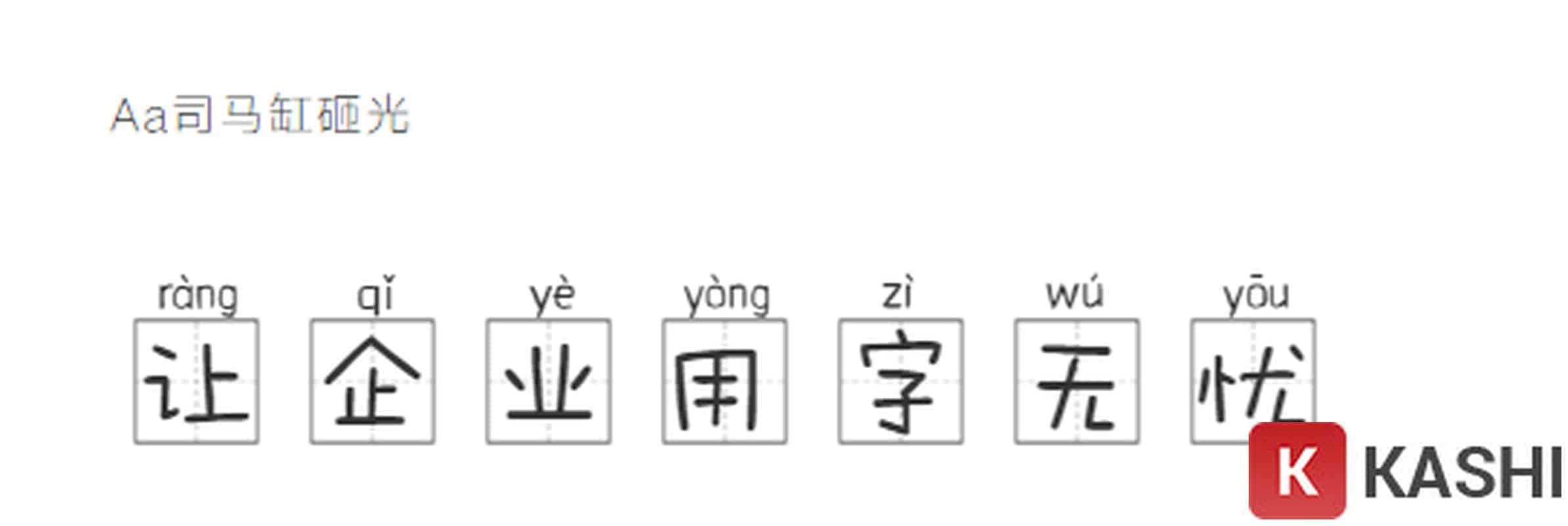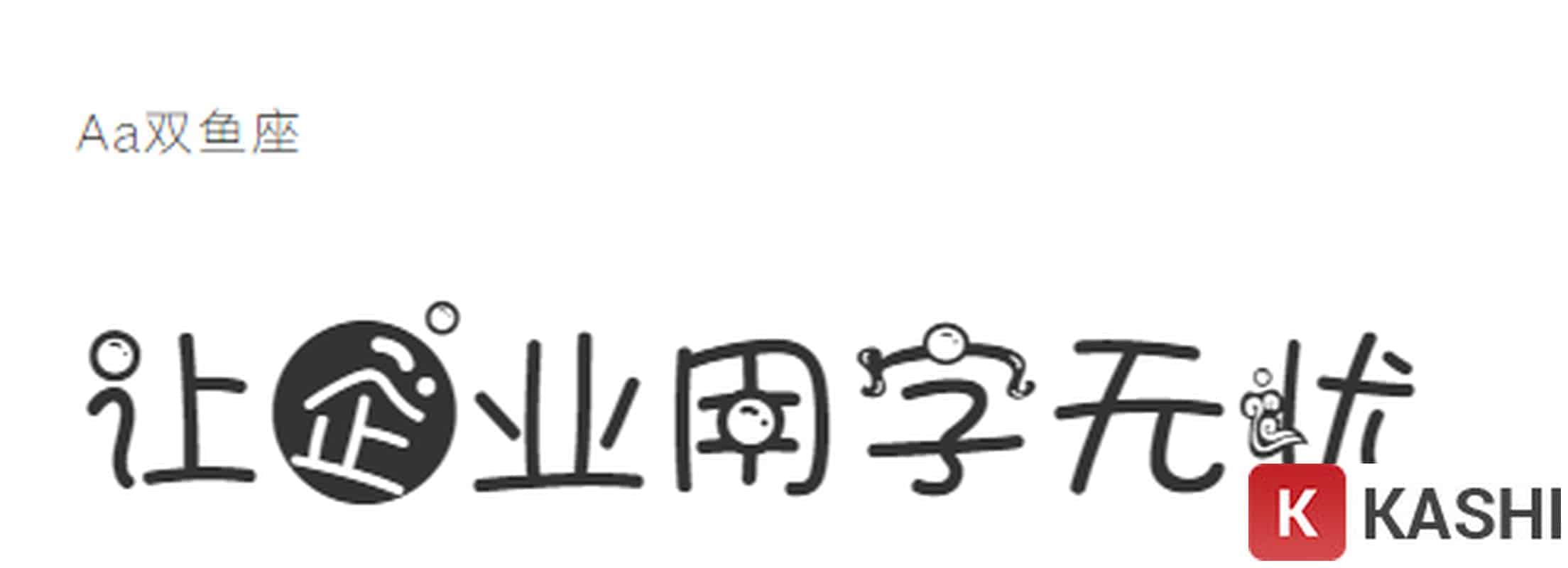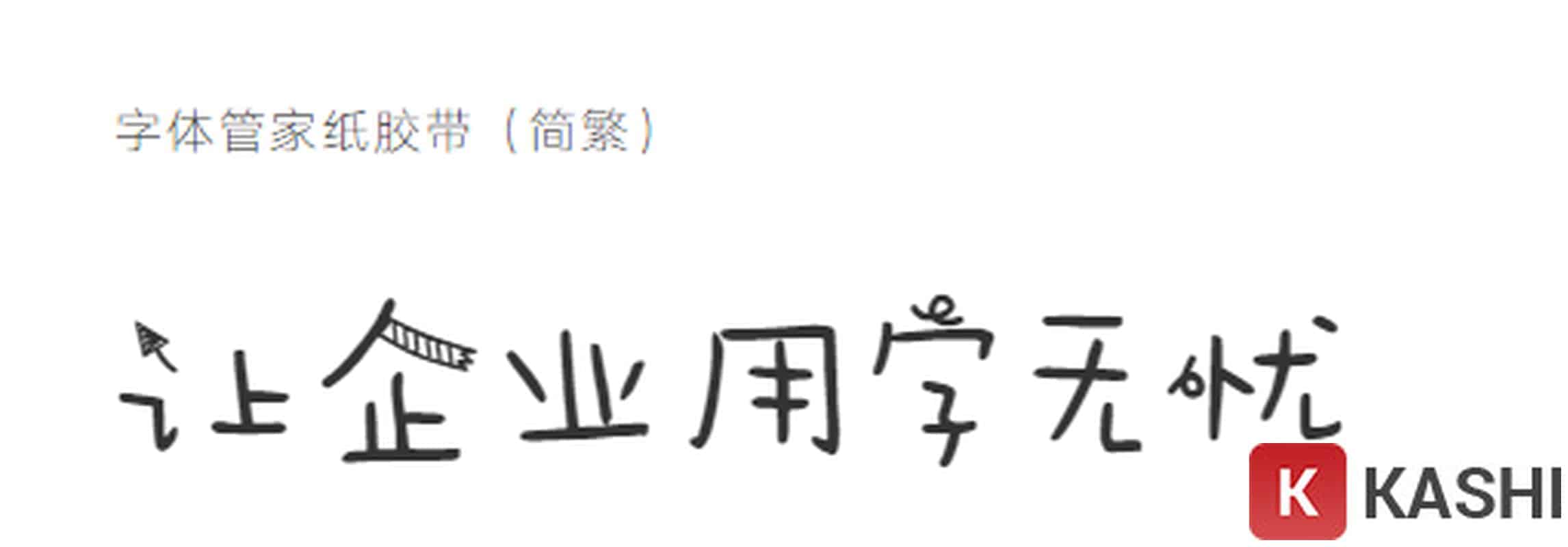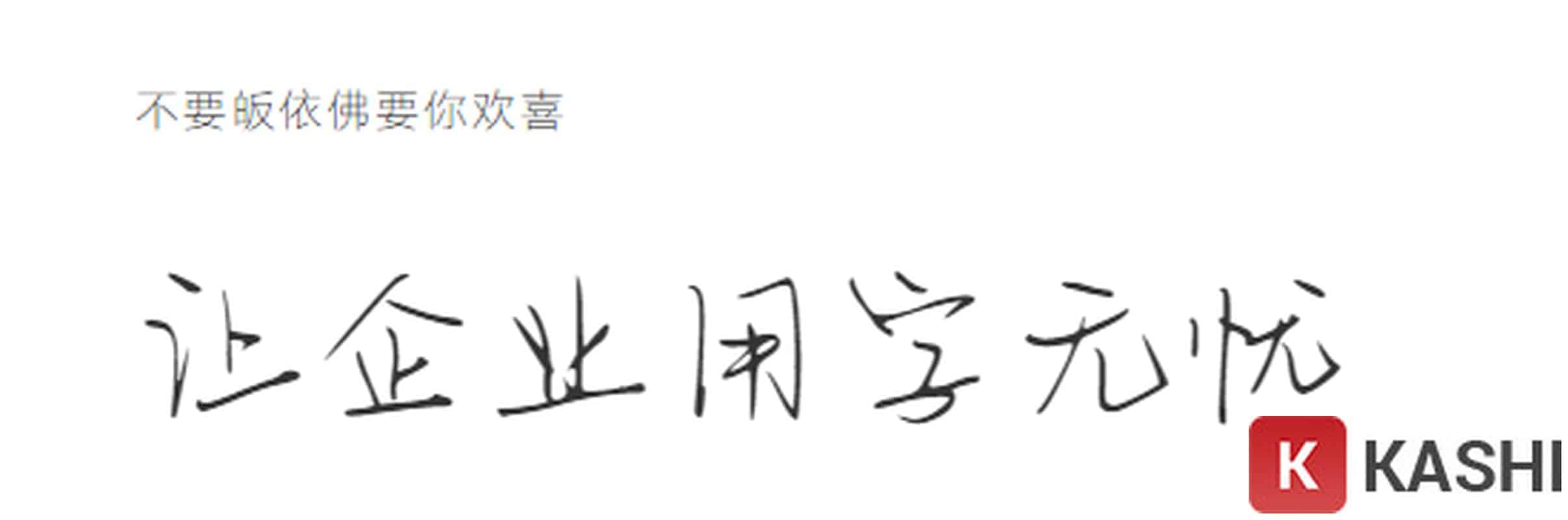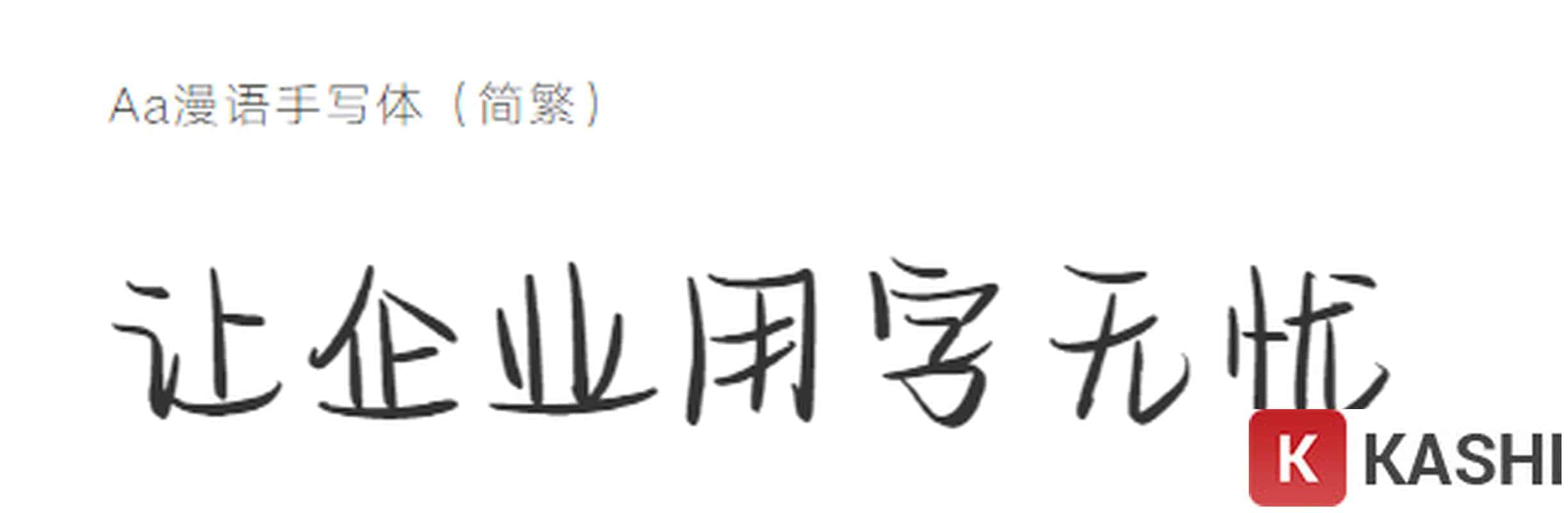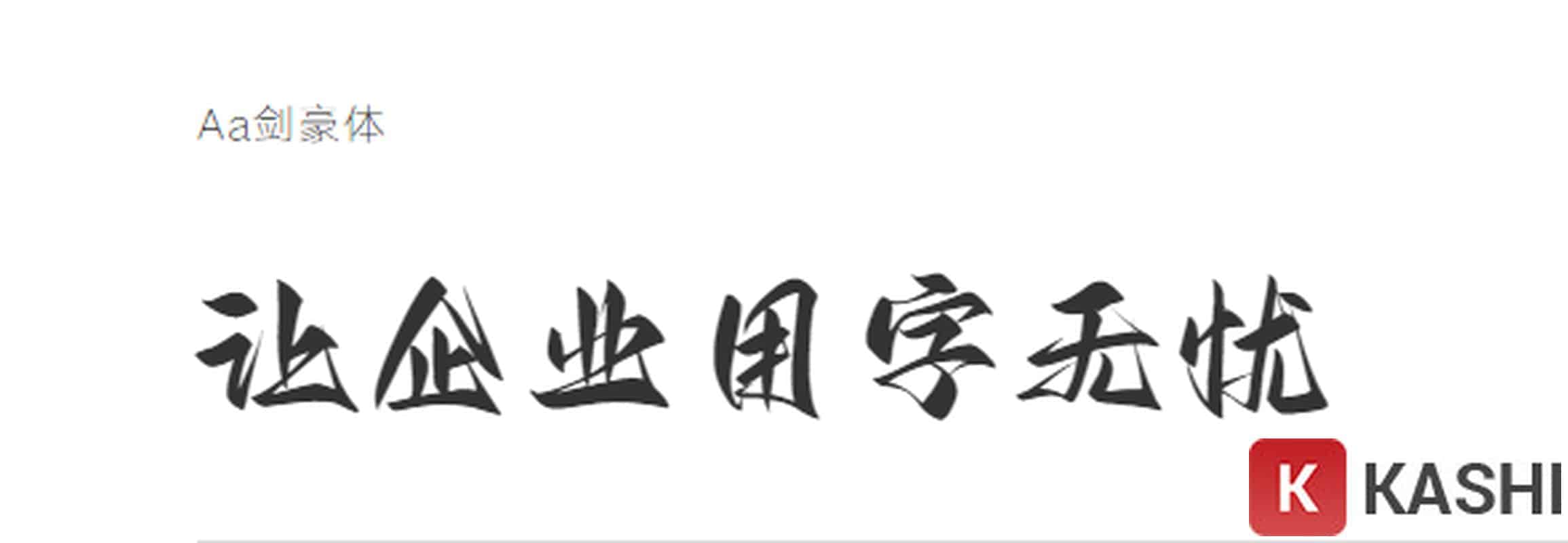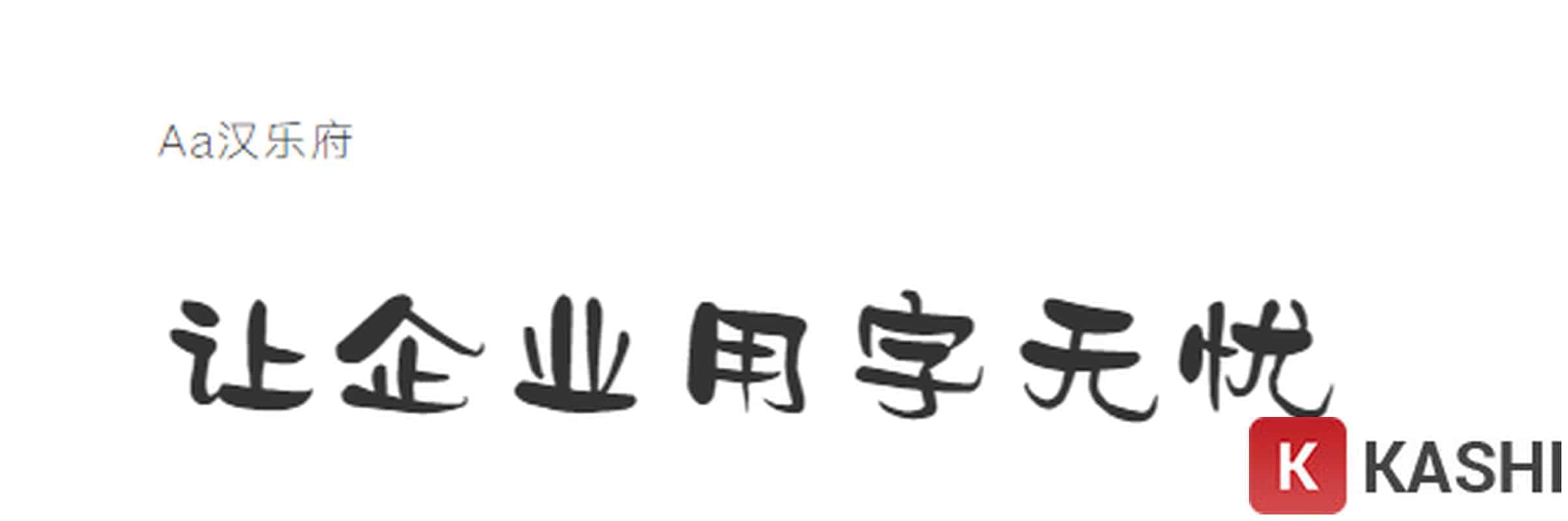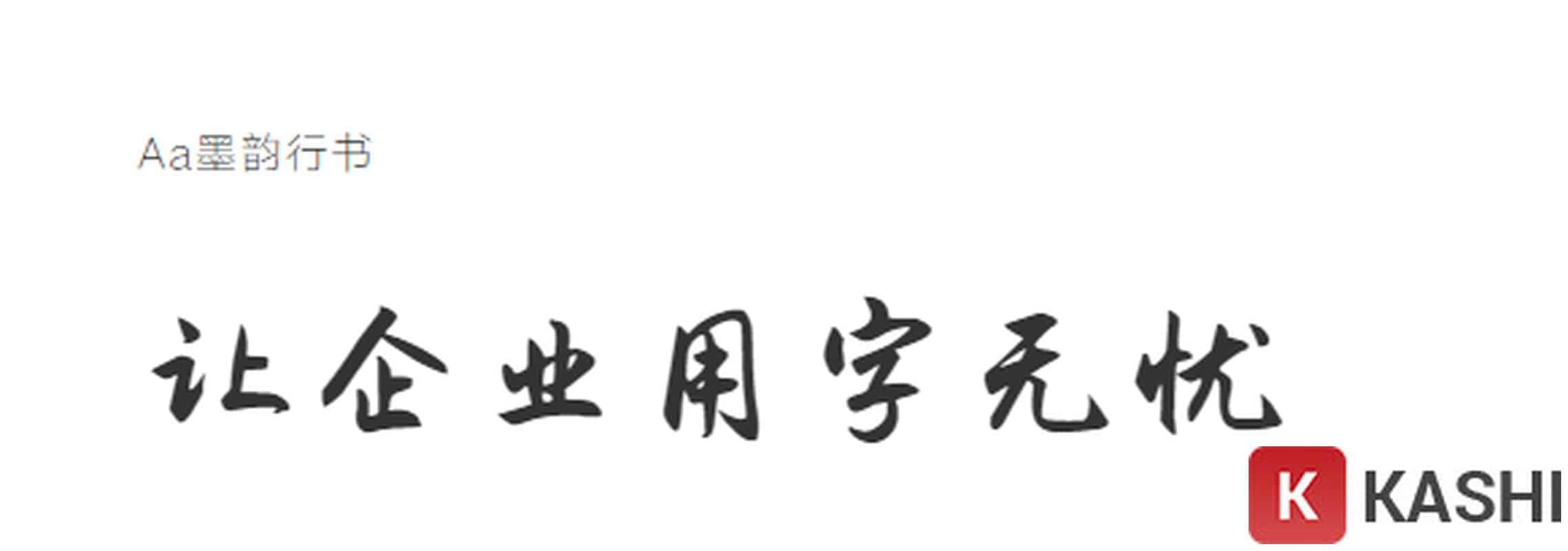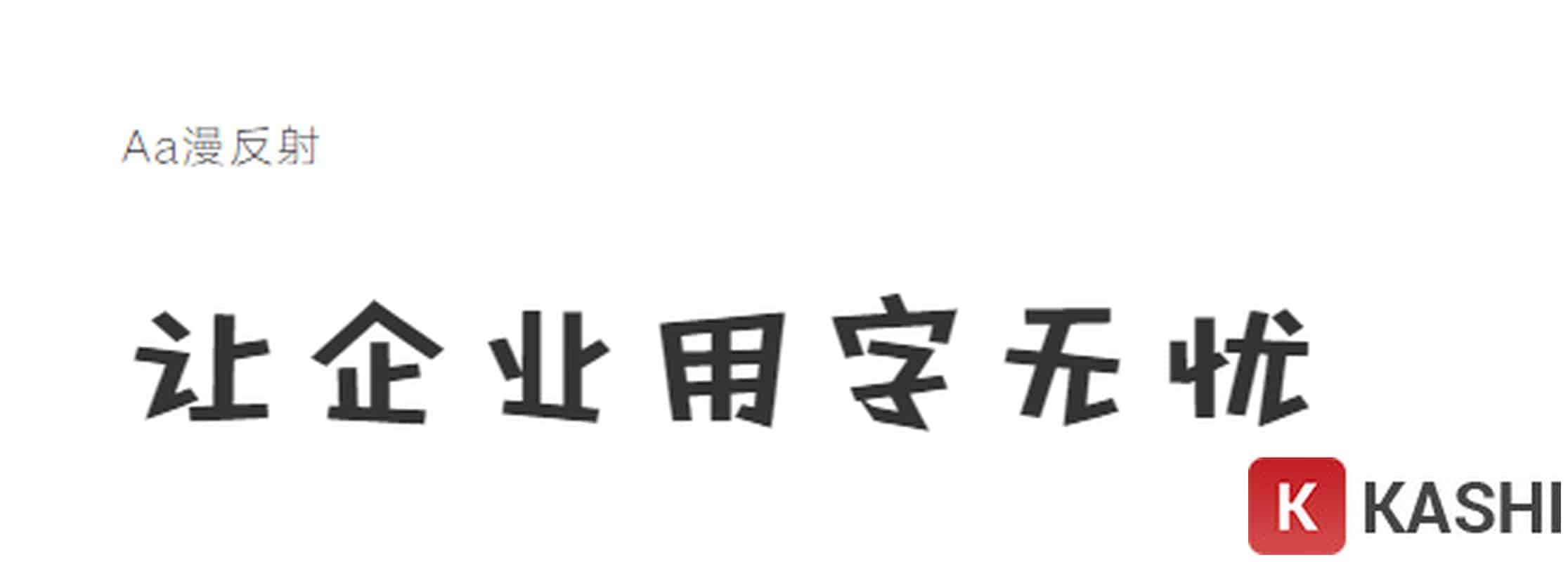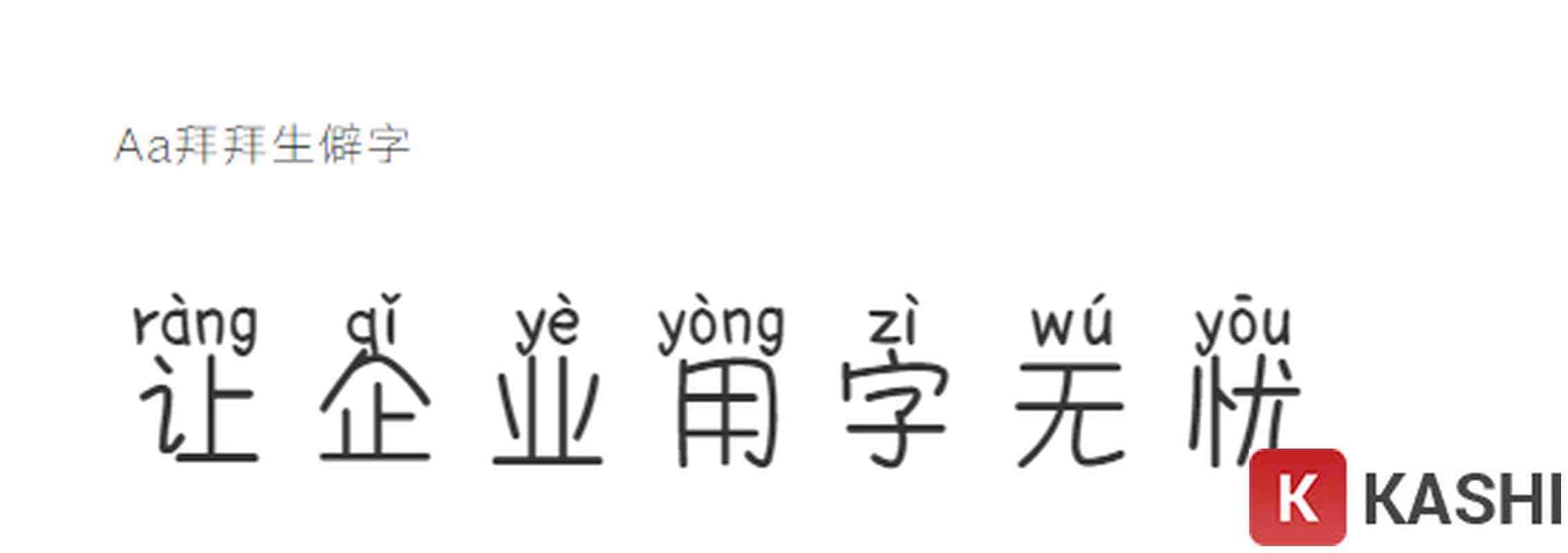
Tổng hợp Font chữ tiếng Trung đẹp và miễn phí
Nếu bạn là người học tiếng Trung hoặc làm việc liên quan đến tiếng Trung, việc cài đặt đa dạng font chữ tiếng Trung là điều cần thiết. Các font chữ tiếng Trung đẹp đáp ứng nhiều nhu cầu khác nhau, từ soạn thảo văn bản đến thiết kế đồ họa. Bài viết này sẽ giới thiệu đến bạn những font chữ tiếng Trung giản thể đẹp, đa dạng chủ đề, hoàn toàn miễn phí.
Bộ sưu tập Font chữ tiếng Trung miễn phí, đa dạng chủ đề
Font chữ tiếng Trung Việt Hóa - Mẫu 1Font chữ tiếng Trung Việt Hóa – Mẫu 1
Font chữ tiếng Trung Việt hóa - Mẫu 2Font chữ tiếng Trung Việt hóa – Mẫu 2
Ngoài ra, bộ font tiếng Trung 方正纤舞体 (Fz- FZXianWTJW) do Foundertype phát hành (font giản thể) cũng đã được Việt hóa và kerning hoàn chỉnh để phù hợp với tiếng Việt.
Các loại Font chữ tiếng Trung phổ biến
1. Font chữ tiếng Trung chuyên nghiệp
Font chữ chuyên nghiệp là yếu tố quan trọng quyết định tính thẩm mỹ và chuyên nghiệp của văn bản, slide trình chiếu, thiết kế đồ họa, đặc biệt là những sản phẩm yêu cầu cao về hình thức.
Font chữ tiếng Trung chuyên nghiệp - Mẫu 1Font chữ tiếng Trung chuyên nghiệp – Mẫu 1
Font chữ tiếng Trung chuyên nghiệp - Mẫu 2Font chữ tiếng Trung chuyên nghiệp – Mẫu 2
Font chữ tiếng Trung chuyên nghiệp - Mẫu 3Font chữ tiếng Trung chuyên nghiệp – Mẫu 3
Font chữ tiếng Trung chuyên nghiệp - Mẫu 4Font chữ tiếng Trung chuyên nghiệp – Mẫu 4
Font chữ tiếng Trung chuyên nghiệp - Mẫu 5Font chữ tiếng Trung chuyên nghiệp – Mẫu 5
2. Font chữ tiếng Trung sáng tạo
Với đường nét uyển chuyển, linh hoạt, kích thước xen kẽ, font chữ sáng tạo mang đến sự mới mẻ so với các font chữ truyền thống. Chúng thường được sử dụng để tạo điểm nhấn độc đáo cho các thiết kế.
Font chữ tiếng Trung sáng tạo - Mẫu 1Font chữ tiếng Trung sáng tạo – Mẫu 1
Font chữ tiếng Trung sáng tạo - Mẫu 2Font chữ tiếng Trung sáng tạo – Mẫu 2
Font chữ tiếng Trung sáng tạo - Mẫu 3Font chữ tiếng Trung sáng tạo – Mẫu 3
Font chữ tiếng Trung sáng tạo - Mẫu 4Font chữ tiếng Trung sáng tạo – Mẫu 4
Font chữ tiếng Trung sáng tạo - Mẫu 5Font chữ tiếng Trung sáng tạo – Mẫu 5
3. Font chữ tiếng Trung thư pháp
Font chữ thư pháp mang tính nghệ thuật cao, được sử dụng rộng rãi trong thiết kế đồ họa, in ấn. Nét đẹp tinh tế và sức ảnh hưởng mạnh mẽ của thư pháp khiến font chữ này luôn là lựa chọn phổ biến.
Font chữ tiếng Trung thư pháp - Mẫu 1Font chữ tiếng Trung thư pháp – Mẫu 1
Font chữ tiếng Trung thư pháp - Mẫu 2Font chữ tiếng Trung thư pháp – Mẫu 2
Font chữ tiếng Trung thư pháp - Mẫu 3Font chữ tiếng Trung thư pháp – Mẫu 3
Font chữ tiếng Trung thư pháp - Mẫu 4Font chữ tiếng Trung thư pháp – Mẫu 4
Font chữ tiếng Trung thư pháp - Mẫu 5Font chữ tiếng Trung thư pháp – Mẫu 5
4. Font chữ tiếng Trung viết tay
Font chữ viết tay đang trở thành xu hướng mới, mang đến sự độc đáo và sáng tạo cho quảng cáo, bài viết. Sự phát triển của công nghệ máy tính giúp font chữ viết tay được tối ưu hóa, đáp ứng nhu cầu đa dạng của người dùng.
Font chữ tiếng Trung viết tay - Mẫu 1Font chữ tiếng Trung viết tay – Mẫu 1
Font chữ tiếng Trung viết tay - Mẫu 2Font chữ tiếng Trung viết tay – Mẫu 2